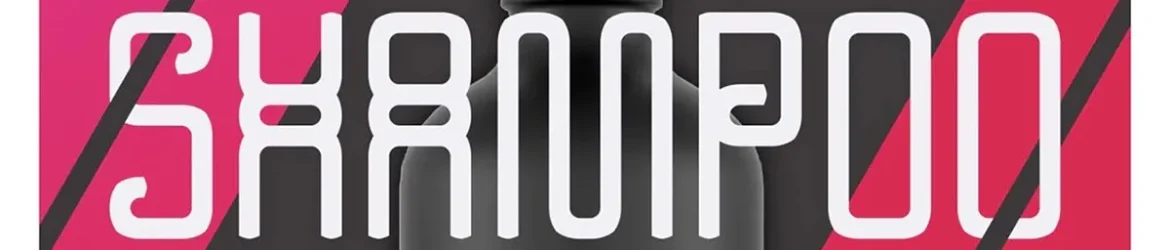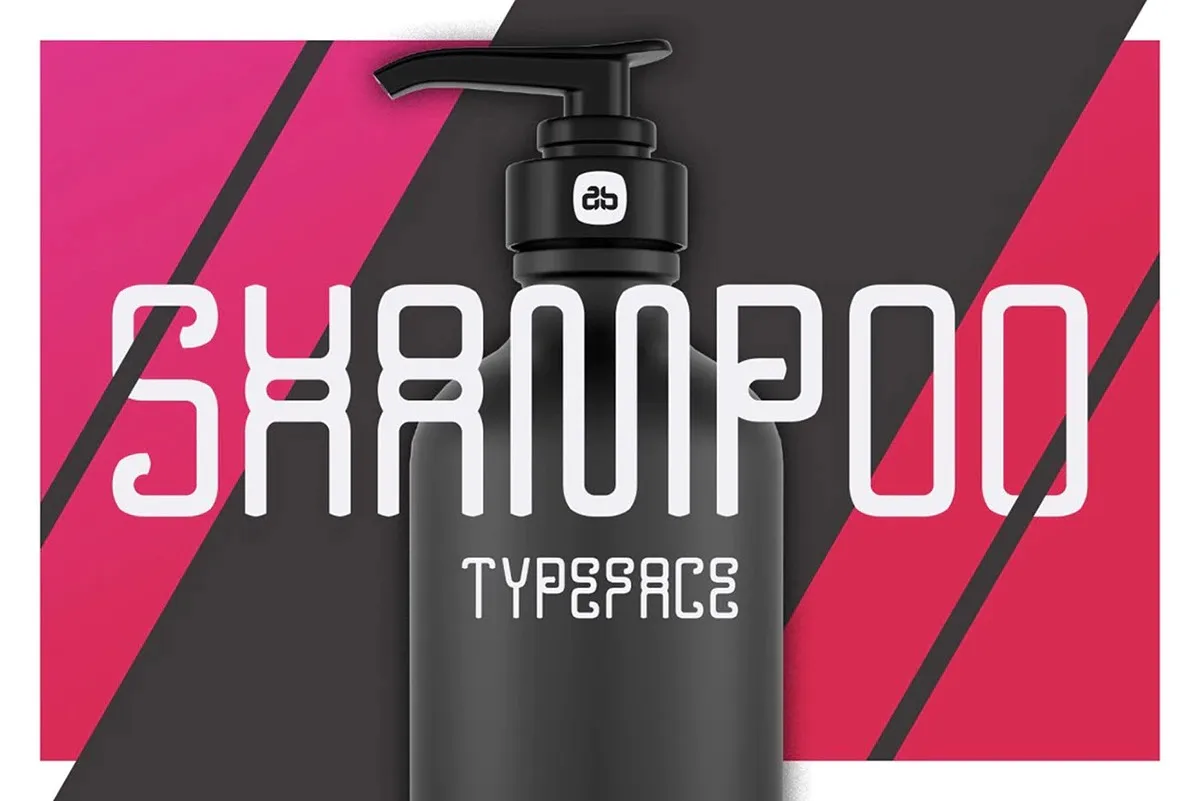
Shampoo Display Font – Fonte Grátis
Shampoo Display Font
A Shampoo é uma fonte moderna sans serif com elementos suaves e belas swashes. Ela combina perfeitamente para estilos futuristas, combinando elegância com simplicidade. Este design único e inovador faz dela uma escolha óbvia para o campo da embalagem, onde ela pode ser usada em rótulos, marcas, embalagens, postais e logos, destacando-se no meio de um ambiente cada vez mais digitizado. Com seu design circular complexo, múltiplas linhas e ponteiros que lembram setas, a Shampoo se destaca como uma opção inovadora para aqueles buscando algo diferente para dar à sua marca ou produto. Esta fonte é perfeita para quem quer destacar-se no mercado com um design único e moderno, conectado ao mundo digital atual.